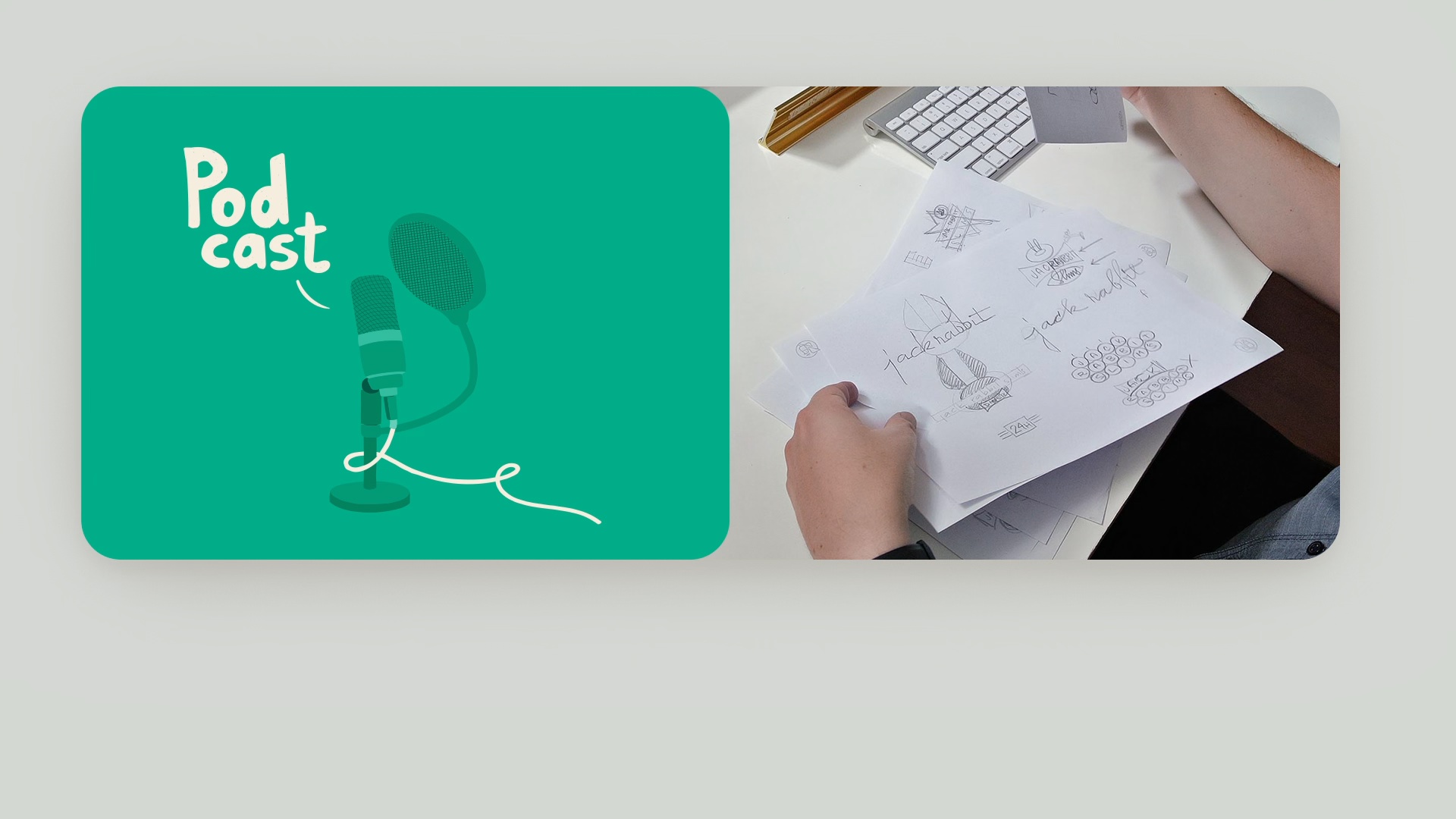
Podcast: A Linguagem Oculta das Formas
Sobre a videoaula: Podcast: A Linguagem Oculta das Formas
“Descubra como o formato de uma fonte pode mudar completamente a personalidade de uma marca em apenas milissegundos. De curvas que transmitem aconchego a ângulos que inspiram precisão, esta reflexão revela a linguagem oculta que conecta nosso instinto primordial com o design e como detalhes invisíveis transformam a forma como nos sentimos ao ver um logotipo.”
Nesta videoaula, Quique Ollervides aborda o tópico: Podcast: A Linguagem Oculta das Formas,que faz parte do curso online da Domestika: Curso guiado: Crie um logotipo com tipografia personalizada. Crie logotipos exclusivos com tipografia personalizada, aprender esboço, vetorização e composição para a marca bem -sucedida.
“Bem-vindos a um novo episódio do Podcast Domestika. onde hoje vamos explorar e decifrar um mistério interessante que acontece sempre que vocês olham para um logotipo. Neste instante. seu cérebro está continuamente avaliando a personalidade. credibilidade e intenções marcas que observa. com base apenas no formato de suas letras. Esse processo é automático e influencia suas Os pesquisadores de Cornell comprovaram isso em 2006. Mostraram logotipos idênticos em conteúdo. mas diferentes em tipografia. e 73% das pessoas atribuíram personalidades completamente distintas a cada um. Seu cérebro proc...”